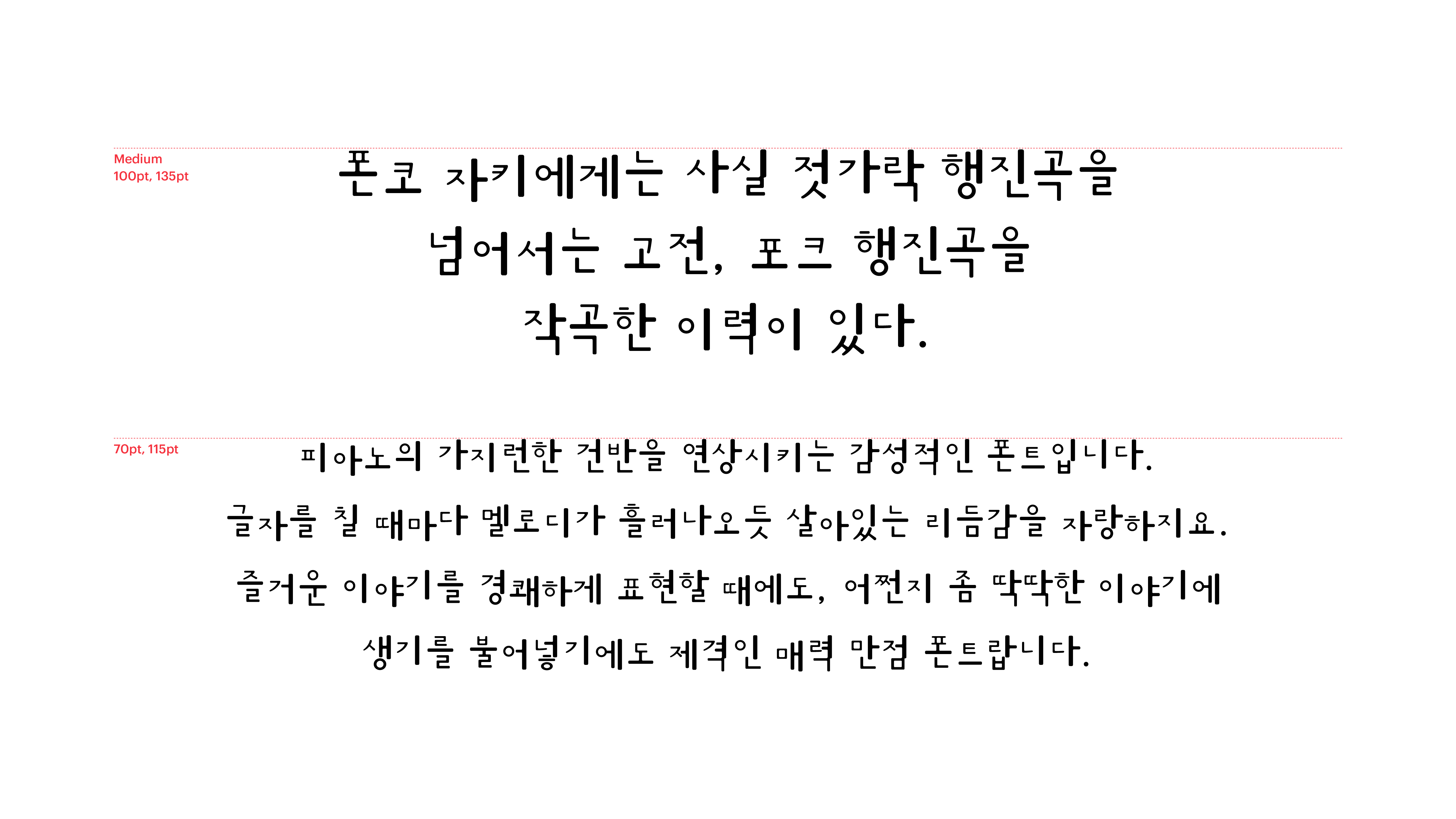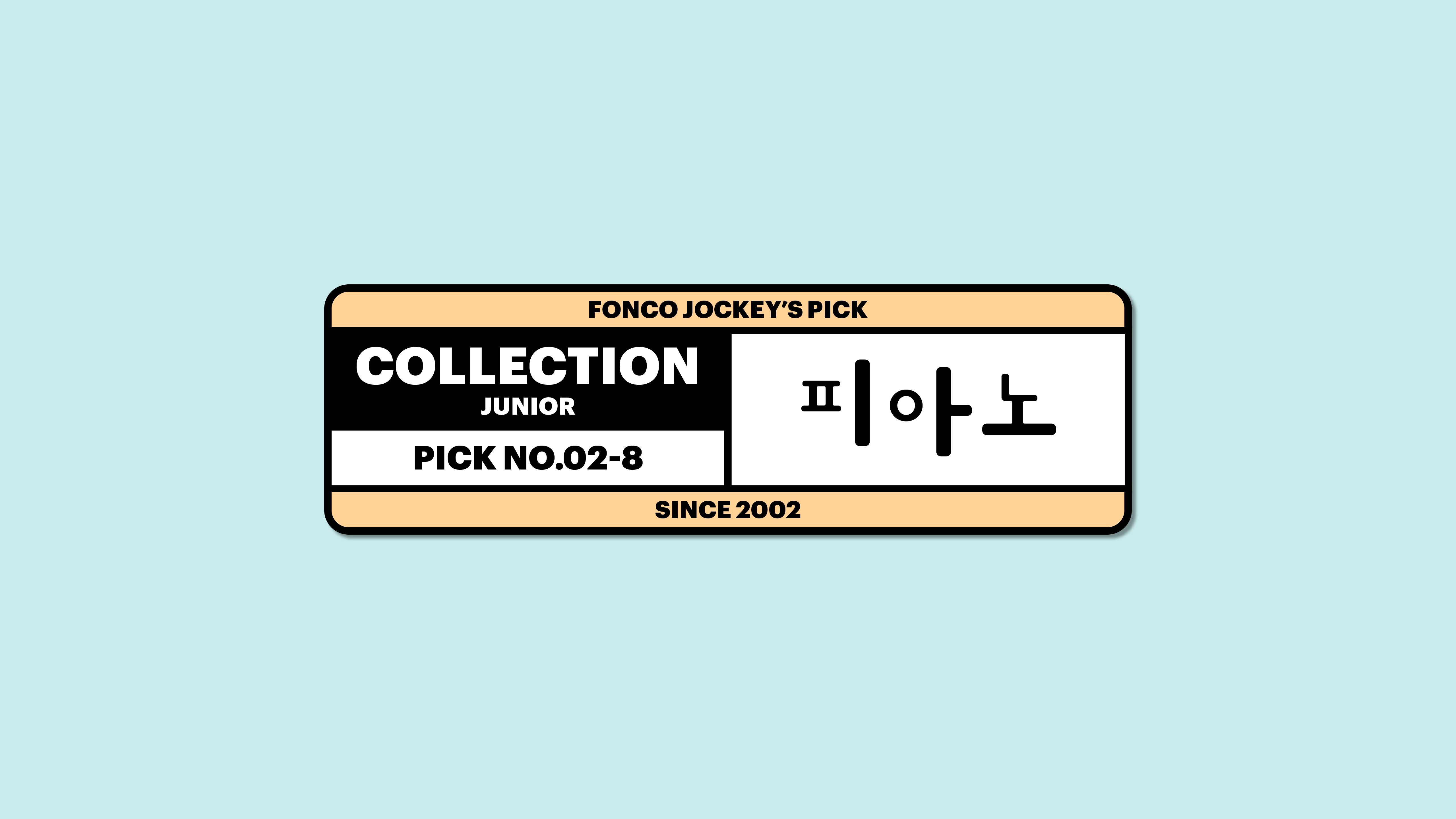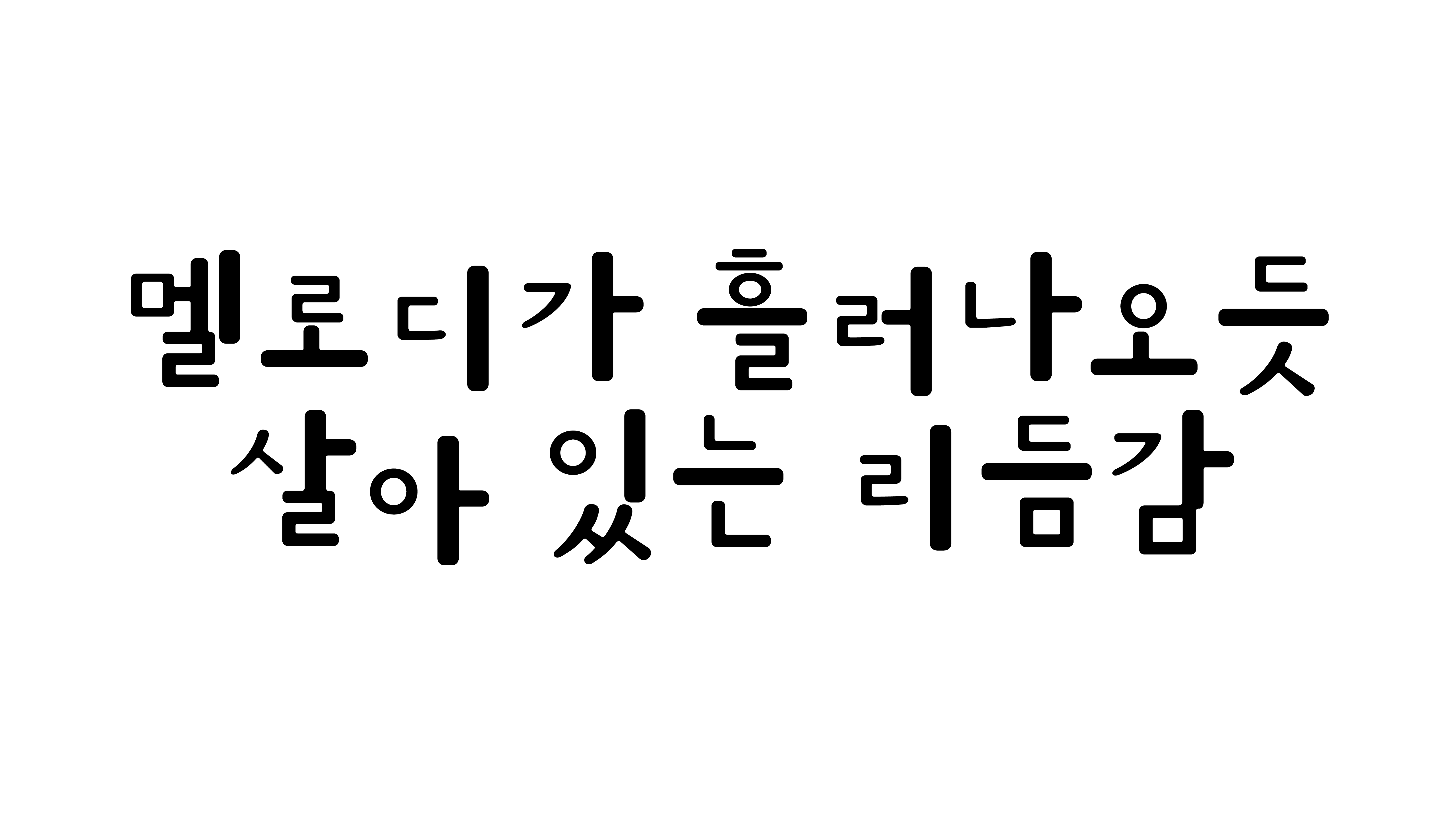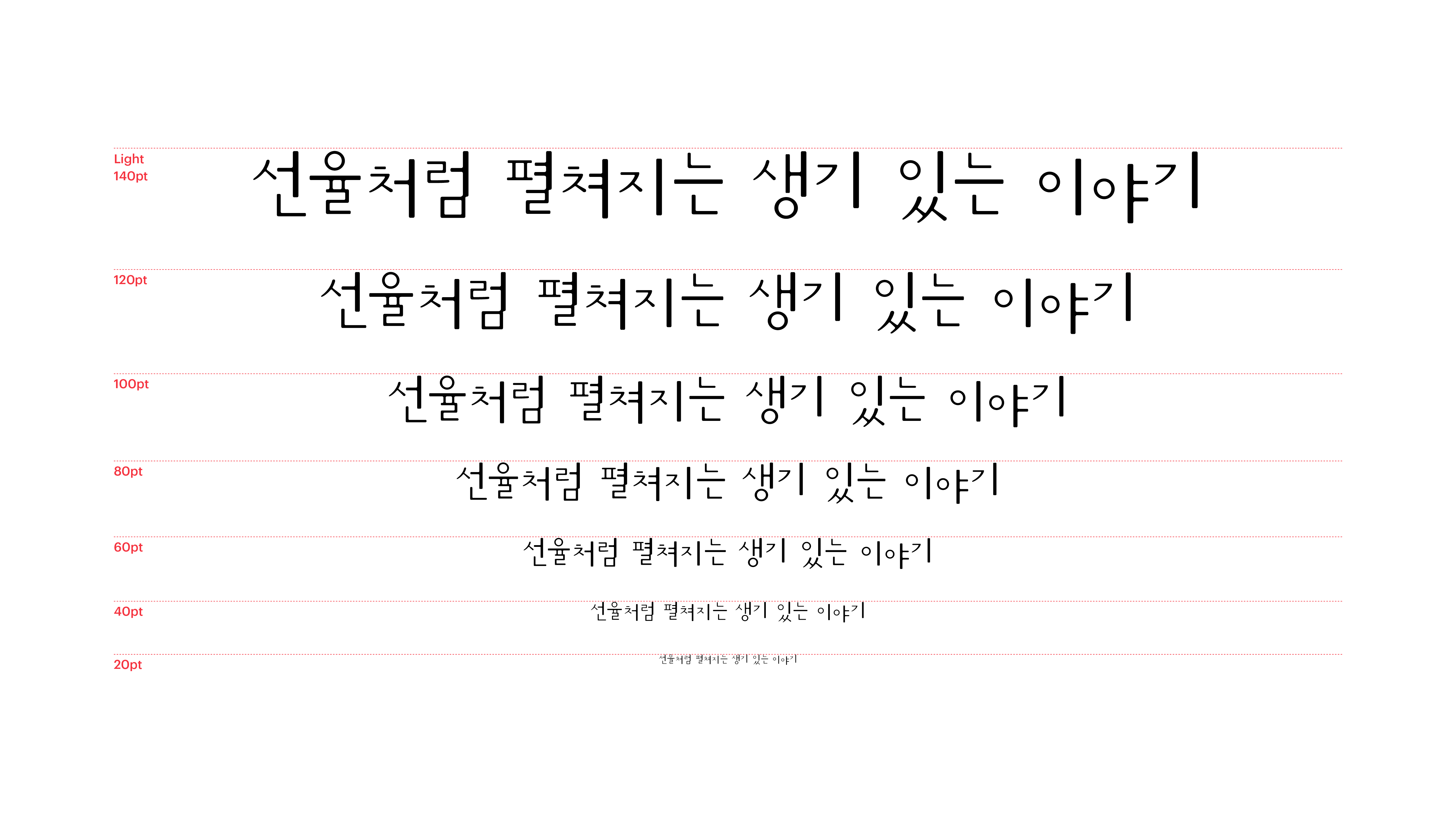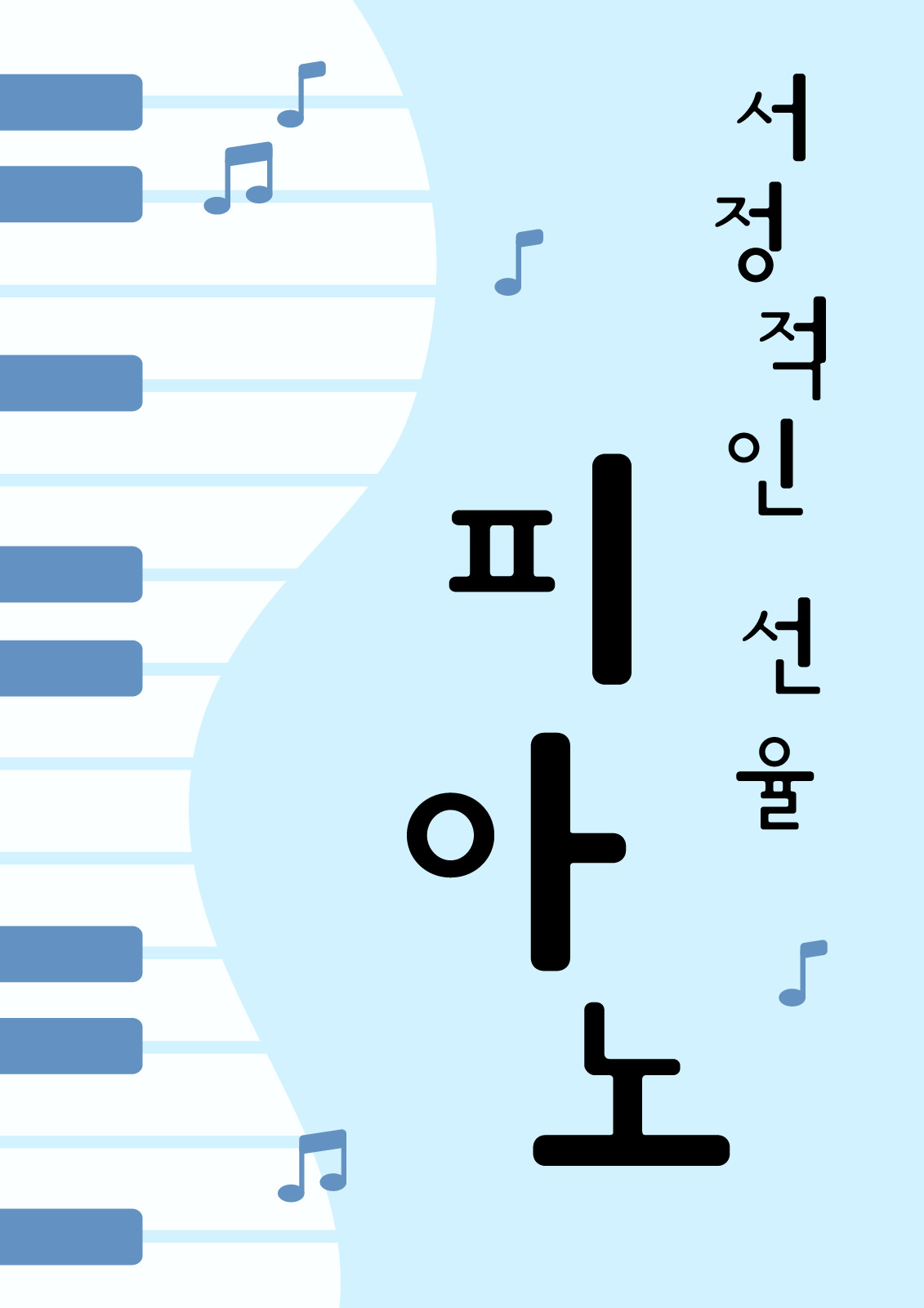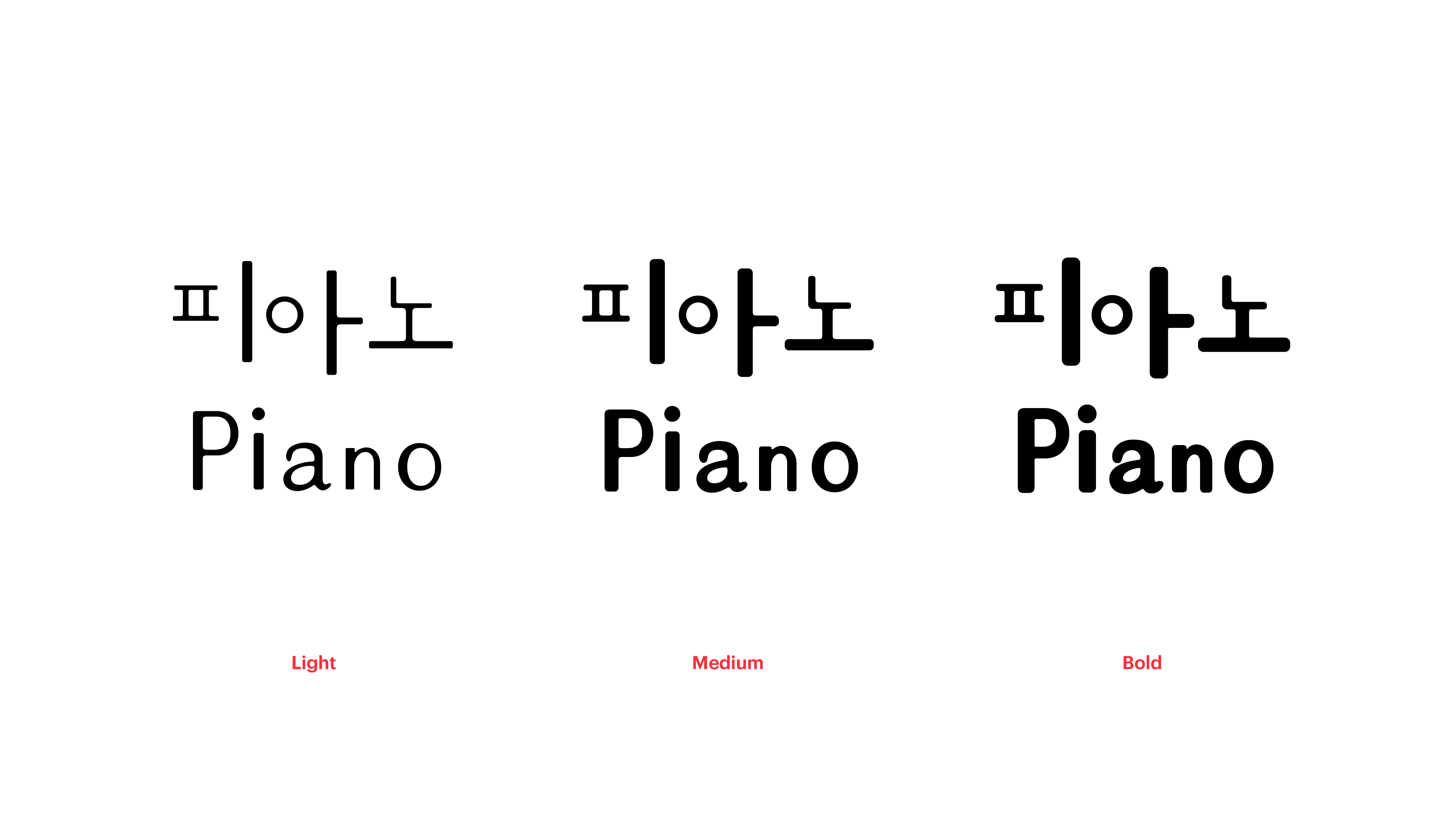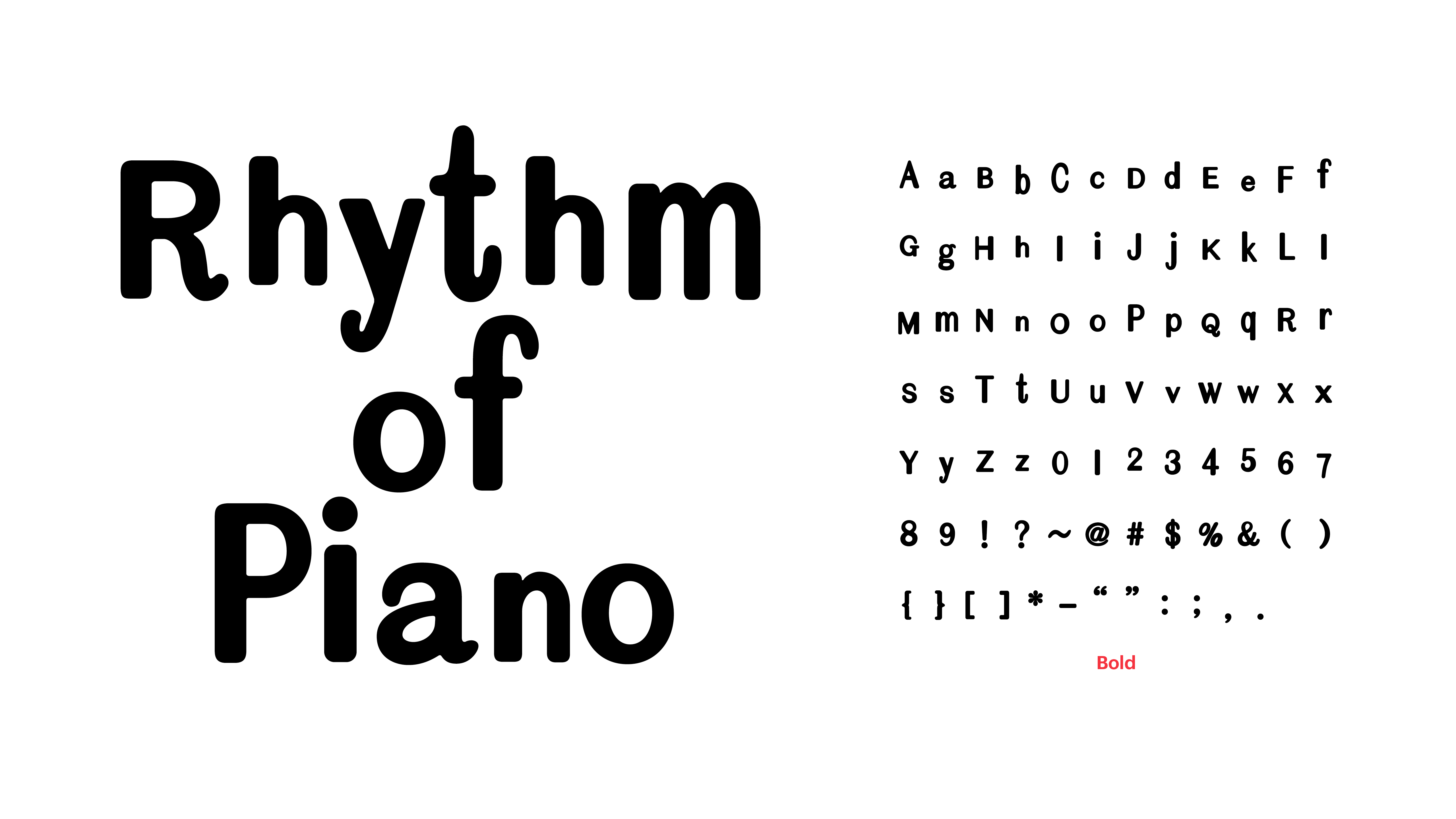
피아노
Yoon 피아노
피아노의 가지런한 건반을 연상시키는 감성적인 폰트입니다. 글자를 칠 때마다 멜로디가 흘러나오듯 살아 있는 리듬감을 자랑하지요. 즐거운 이야기를 경쾌하게 표현할 때에도, 어쩐지 좀 딱딱한 이야기에 생기를 불어넣기에도 제격인 매력 만점 폰트랍니다.